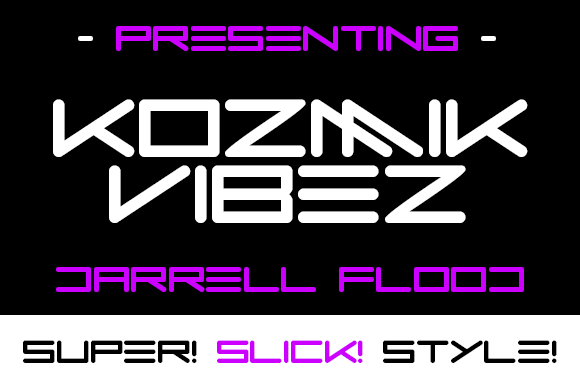
Kozmik Vibez - это удивительно смелый шрифт.
С влиянием робототехники и почти геометрическими вибрациями, этот шрифт идеально подходит для обложек научно-фантастических фильмов, тем парков приключений, космической деятельности и других подобных проектов!